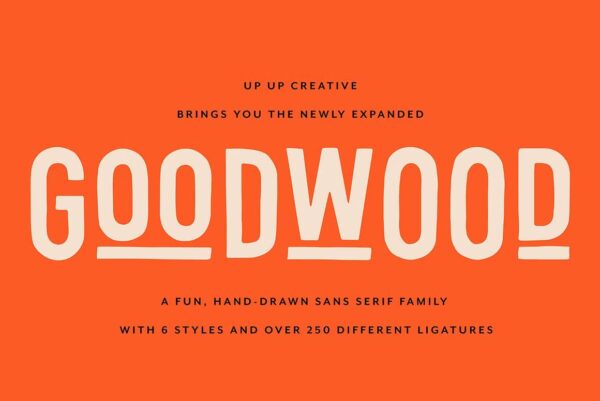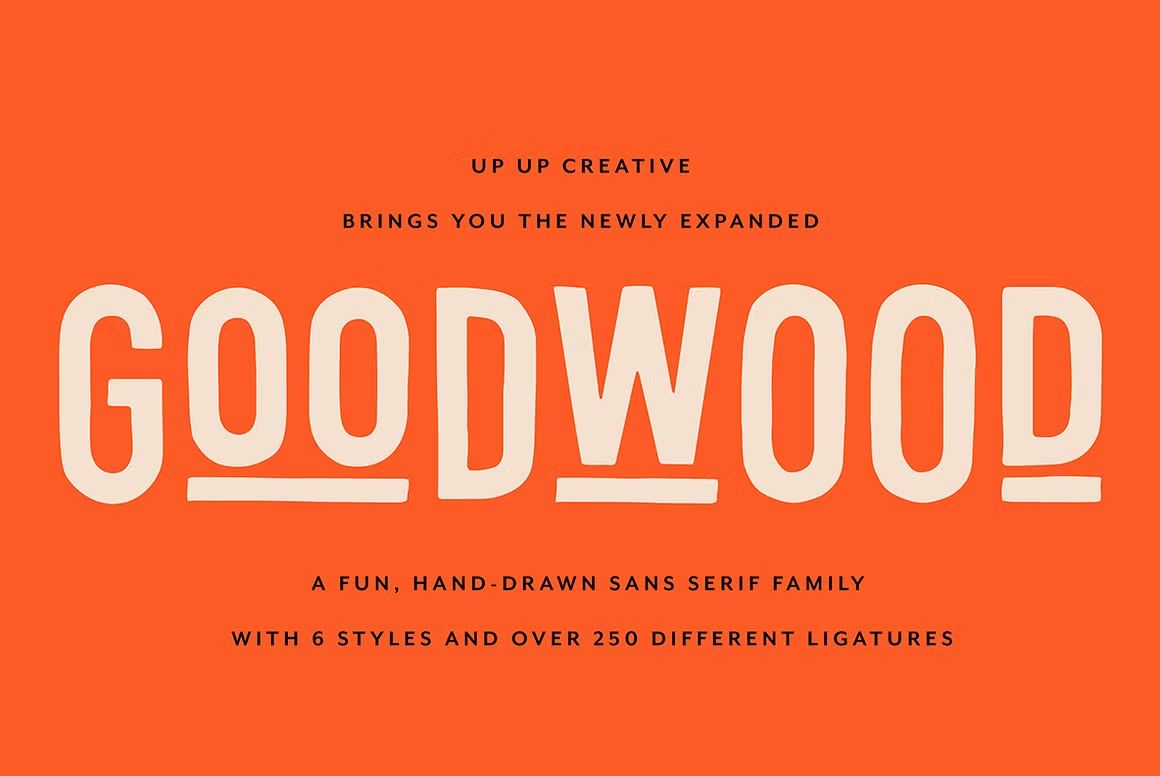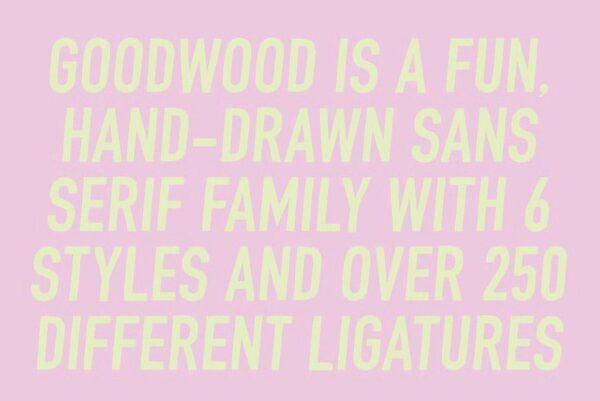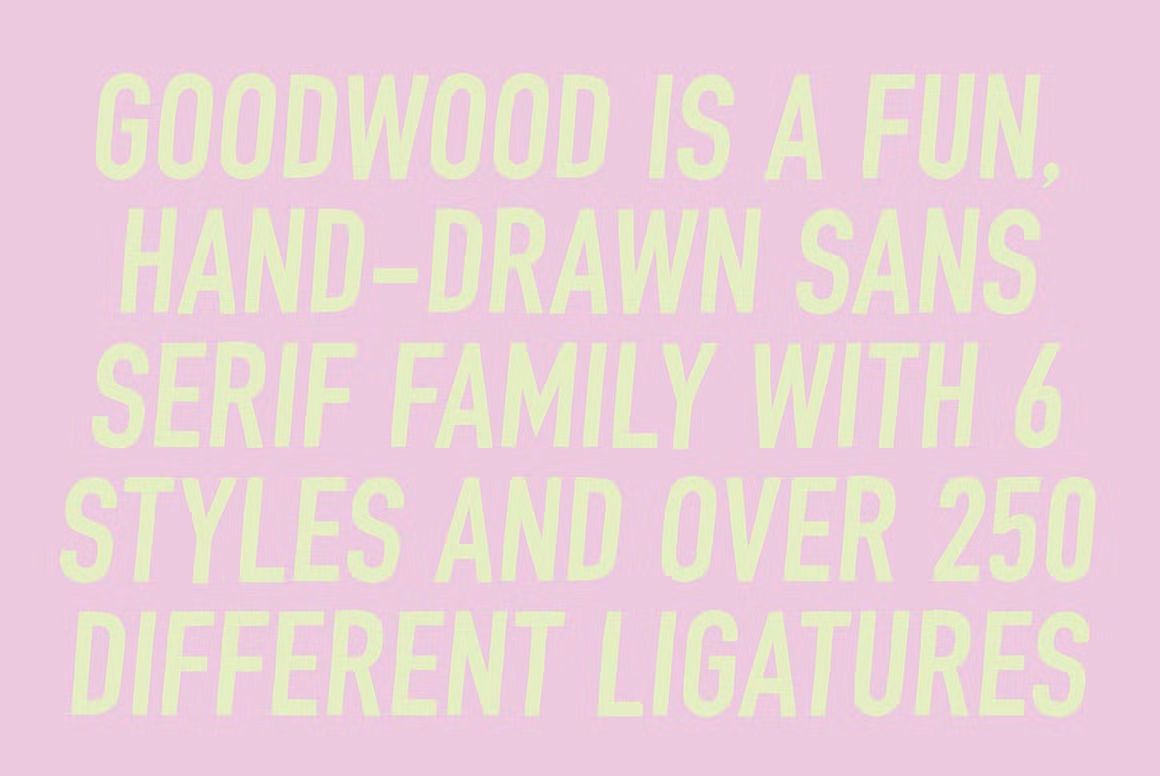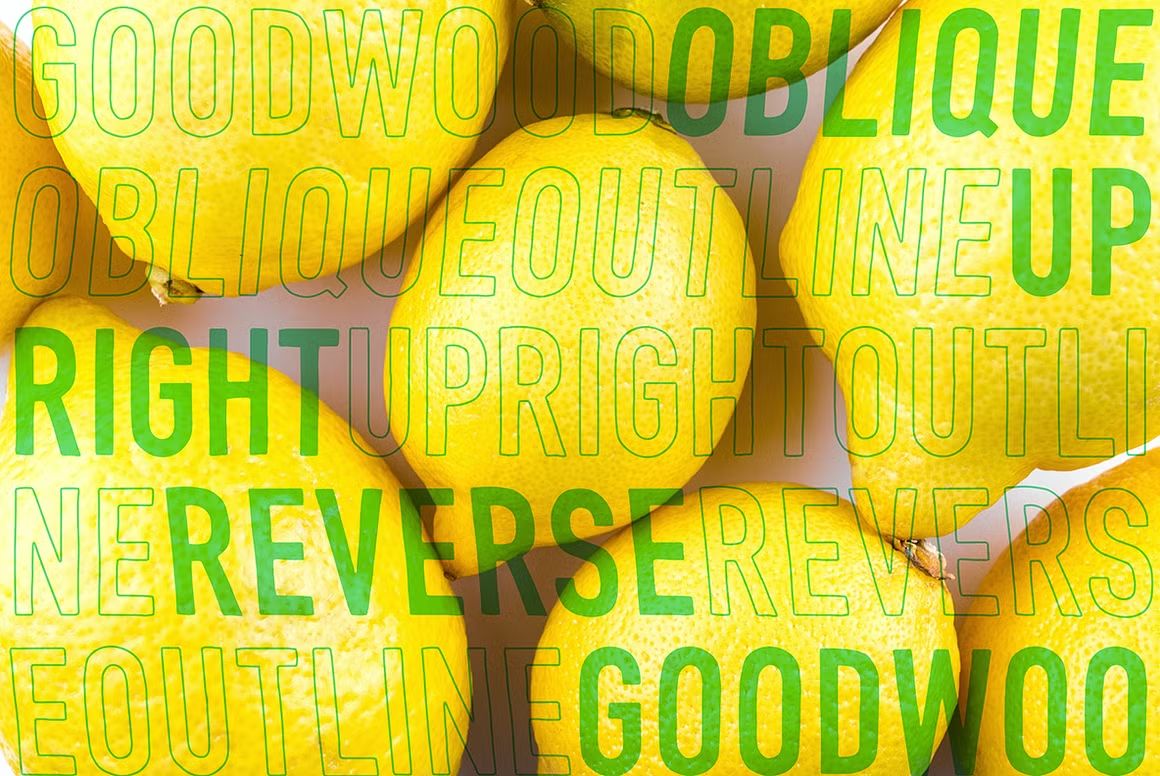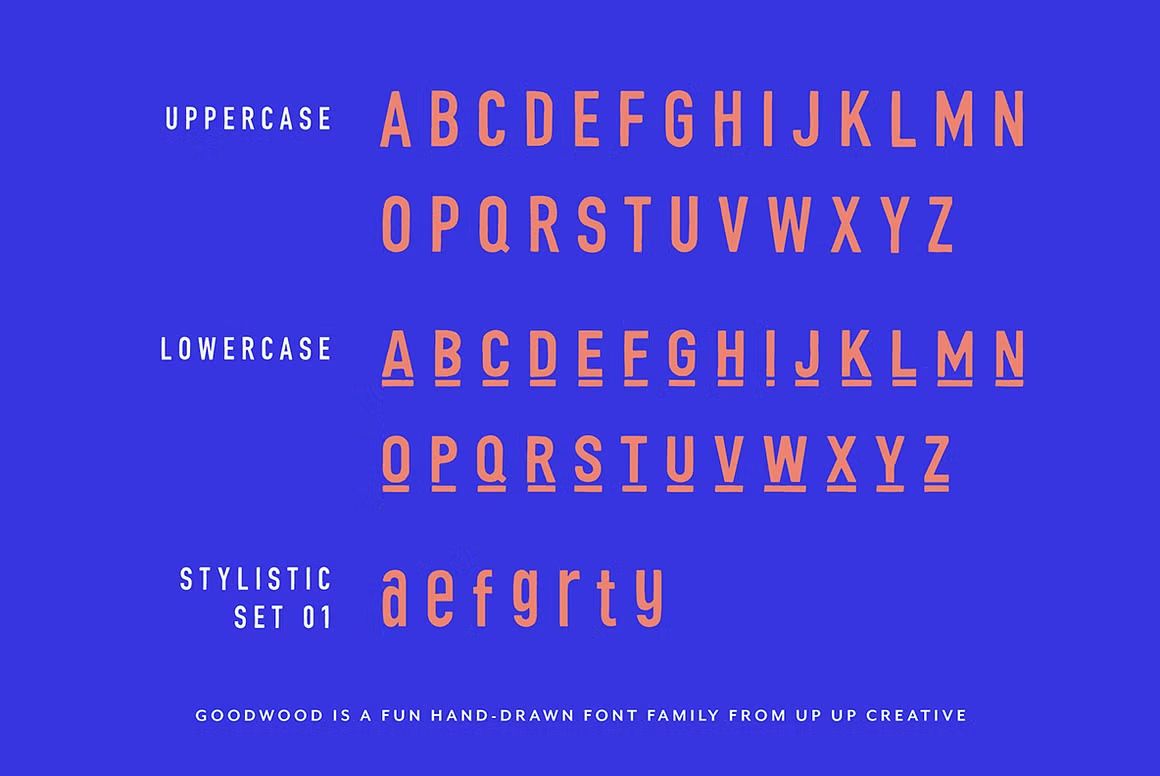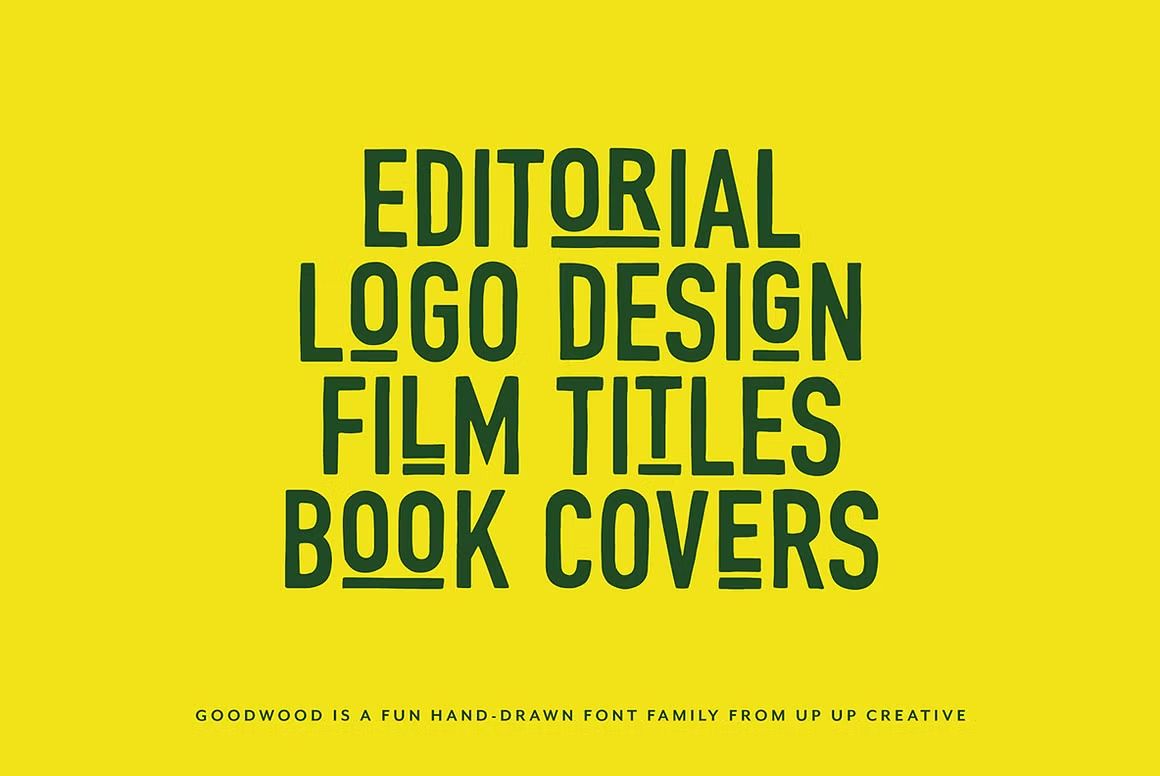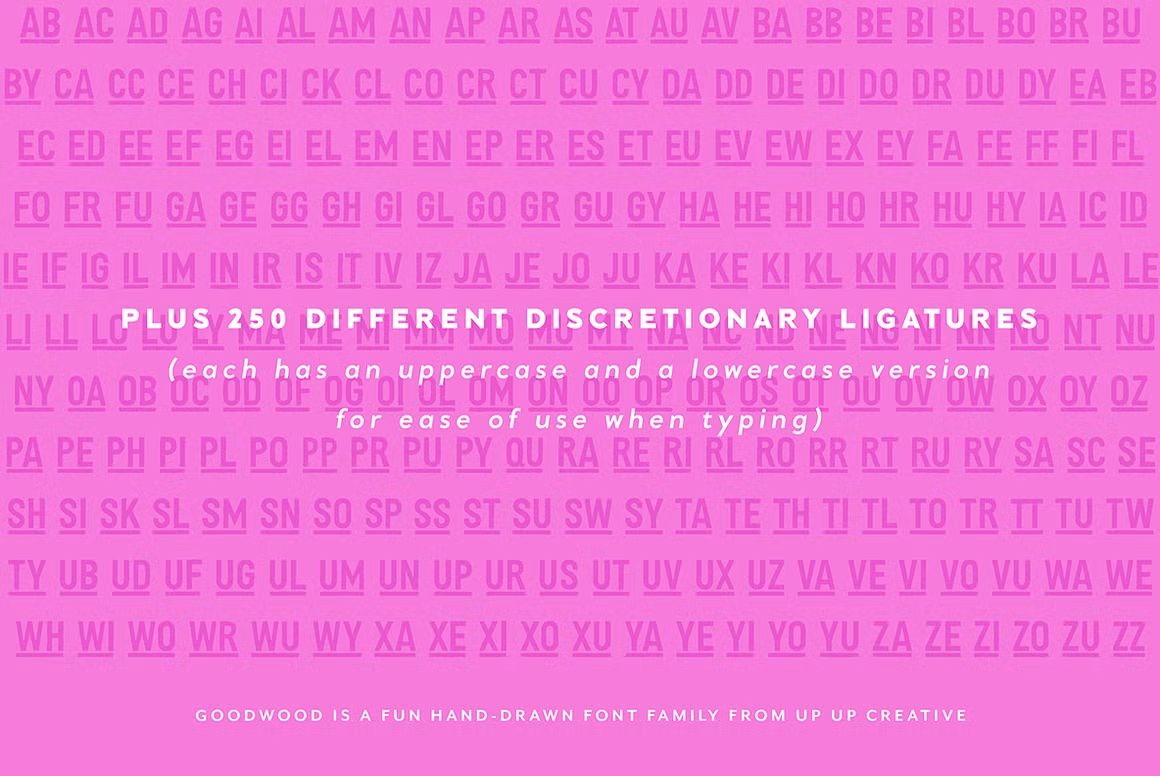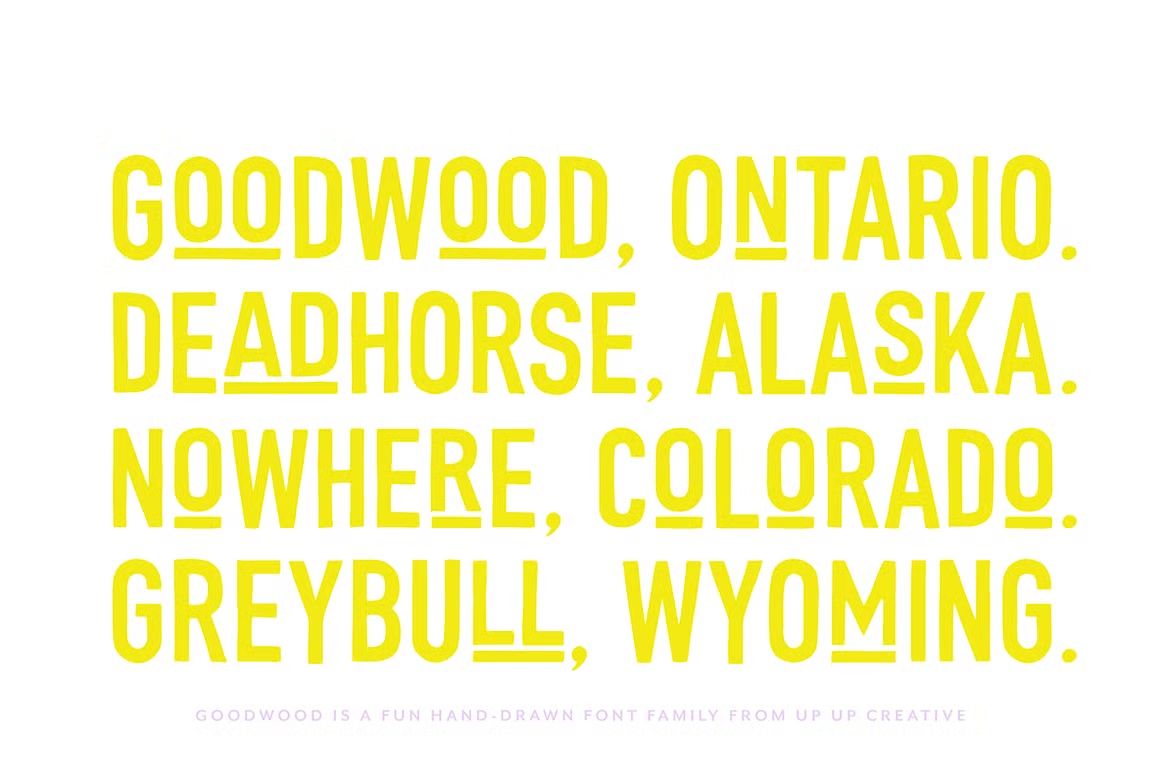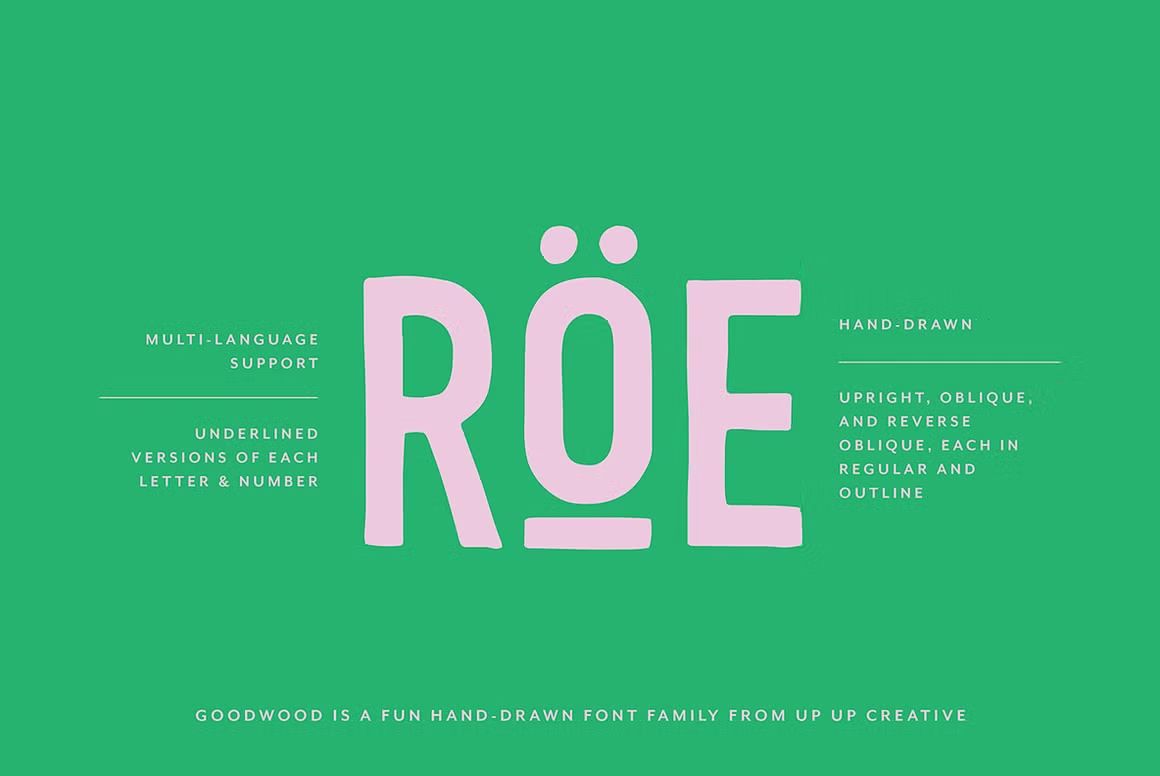
Goodwood – Sans Serif Font
Goodwood adalah font sans serif modern dan bersih, cocok untuk branding, desain digital, dan editorial. Format OTF/TTF/WOFF, siap digunakan.
Goodwood adalah font sans serif modern dengan tampilan bersih, solid, dan serbaguna. Didesain dengan bentuk huruf yang proporsional dan mudah dibaca, Goodwood cocok untuk branding, editorial, kemasan produk, desain web, dan presentasi bisnis. Font ini memadukan kesederhanaan dengan profesionalisme, menjadikannya pilihan tepat untuk berbagai kebutuhan desain.
• Sans serif modern dengan tampilan bersih dan profesional
• Cocok untuk branding, editorial, dan UI/UX
• Termasuk huruf kapital, kecil, angka, dan simbol